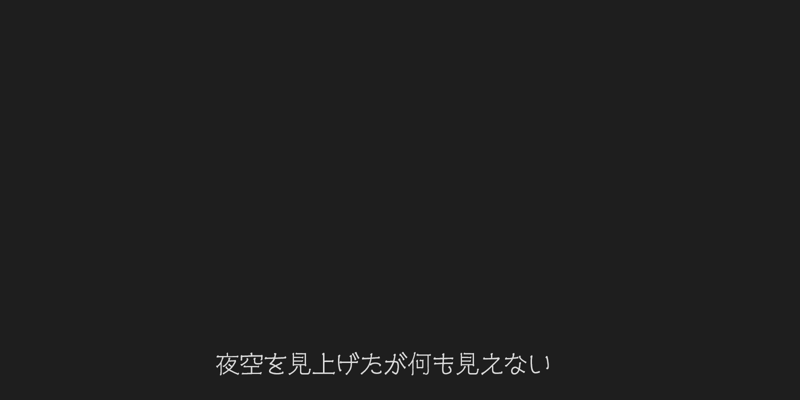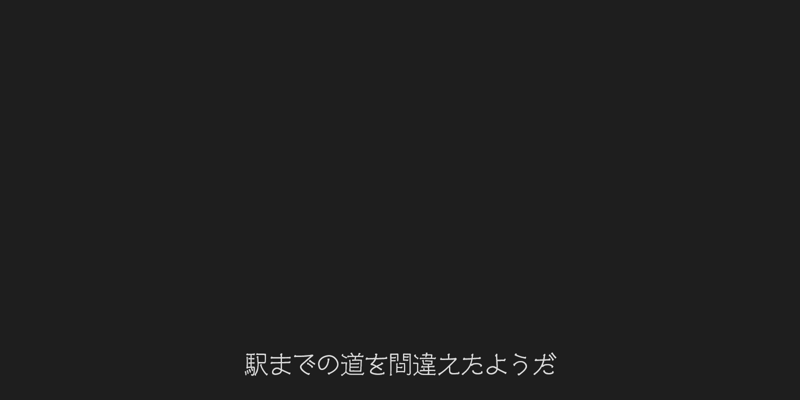
字幕デザインのフォント
シネマレター フォントの作例
シネマレター フォントの作例です。
概要
映画の字幕の文字のデザインのフォントです。
ニューシネマと比較すると、若干細字でスリムな印象があります。
作例
デフォルトの状態では字間が詰まった感じの印象です。読みやすさを考慮した場合は字の間隔を若干調整したほうが良いかもしれません。
シネマレター フォントの作例:画像1
ニューシネマBのように漢字は略字になっていません。
シネマレター フォントの作例:画像2